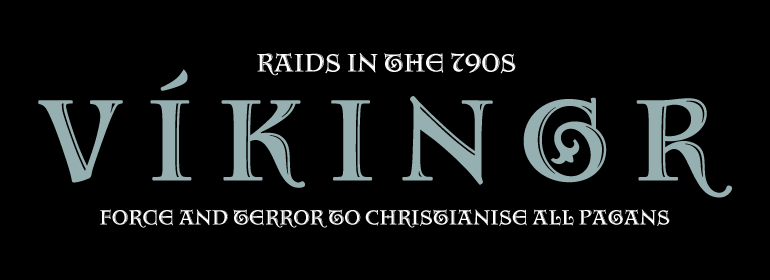
Aquitaine™ Initials
字体品牌: ITC(Monotype) 设计师:Albert,Steven 字体分类: 字体属性:外文 字符集:Unicode 发布时间: 2018
Aquitaine是美国设计师Steven Albert的作品。精美细致的首字母具有独特的风格,而且还具有微妙的历史和宗教色彩。字里行间都应使用更加素净的字母,这样刚好可以通过更复杂的替代字符作为首字母进行完美的补充。
Aquitaine is the work of American designer Steven Albert. The beautifully detailled initials display a unique style which can also carry subtle historical and religious overtones. Words and lines should be set with the plainer alphabet, which is complemented perfectly by the more intricate alternate characters as initials.